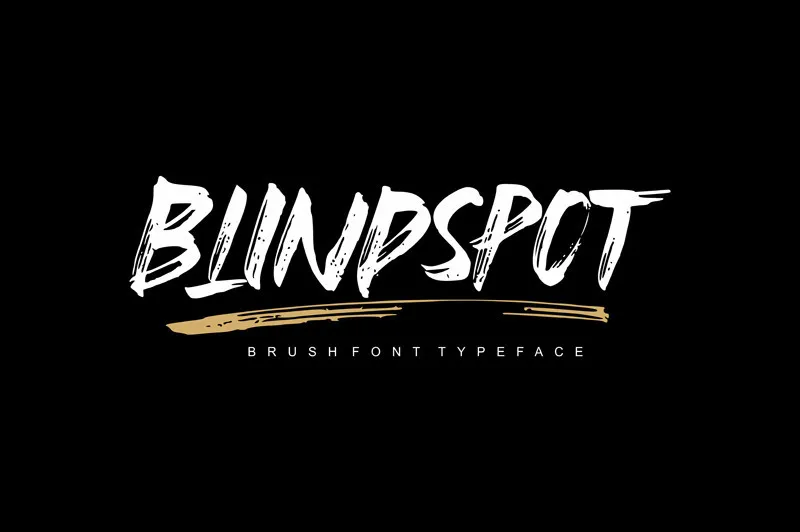
Blindspot Brush Font – Download Grátis
Estamos muito felizes por você dar uma olhada na Blackway Font. Esta é uma fonte brush escrita a mão com textura de realidade dos pincéis. A Blindspot Brush é uma farta assinatura para decoração que permite criar um sentido de letra escrita à mão com um pincel humano. Esta fonte tem um fluxo suave, então você pode usá-la em grandes textos se quiser dar um toque personalizado. É uma excelente opção para logotipos, headlines e embalagens. Você também pode usá-la em longos textos onde você precisa dessa aparência casual escrita à mão. Ela combinará bem com fontes sans-serif e serif. Seja qual for o projeto, esta Blindspot Brush é uma escolha perfeita, pois traz um toque único e autêntico para sua criação. Seja ela um logo chamativo ou um texto elaborado, você vai adorar a experiência de usar essa fonte elegante e fluida. Para os amantes do estilo artesanal e moderno em uma única fonte, esta é definitivamente uma grande escolha!